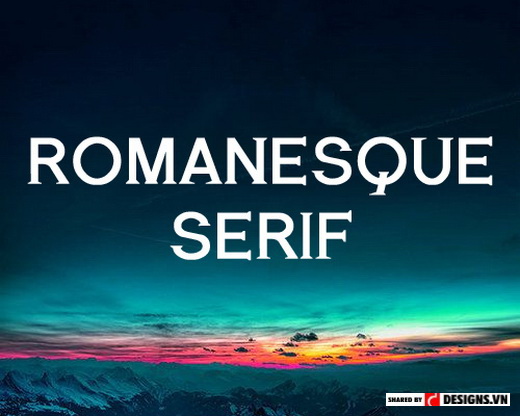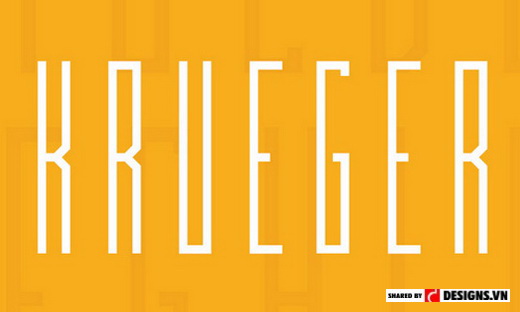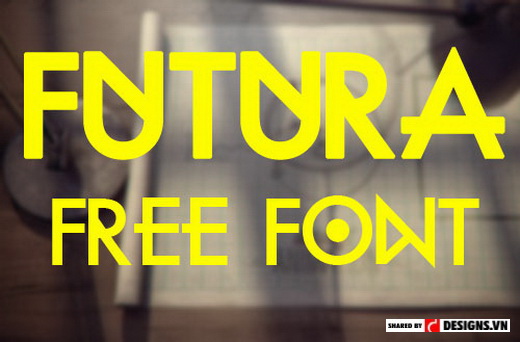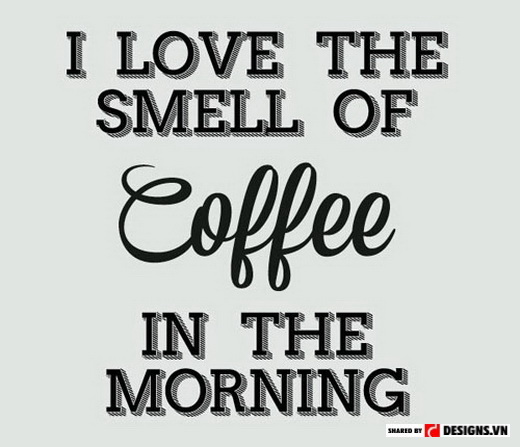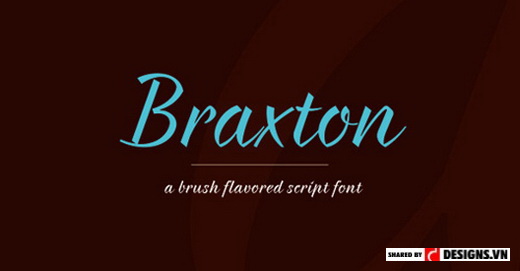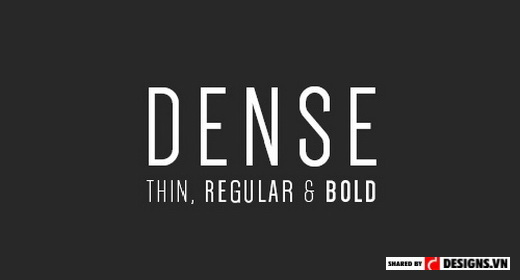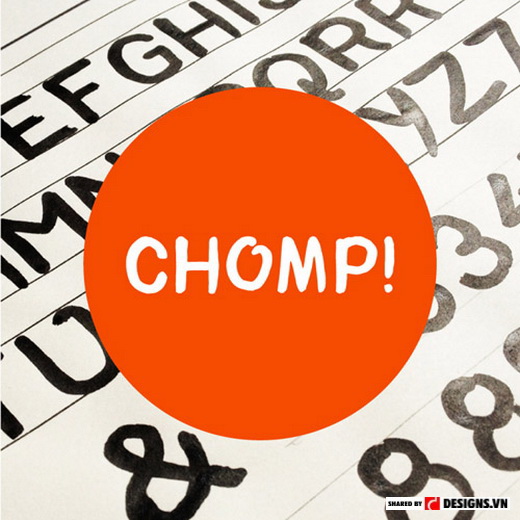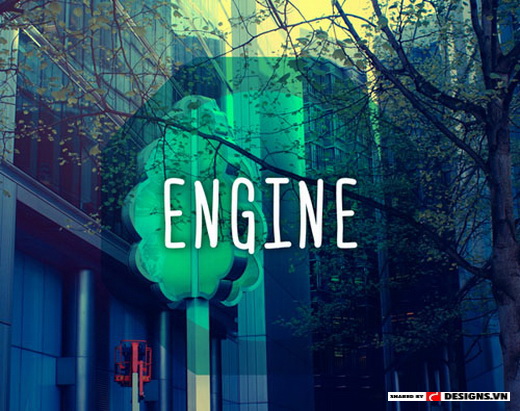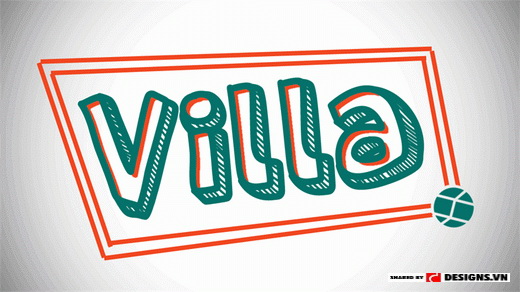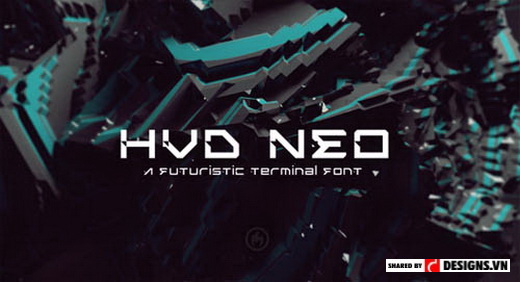
Download 26 font chữ đẹp chọn lọc
1. Romanesque Serif
Romanesque được phát triển từ font chữ Serif, dựa trên cảm hứng về những ký tự La Mã khắc trên bia đá của các ngôi mộ cổ. Download font chữ đẹp này.
2. Serious man
Font chữ cứng cáp dành cho các thiết kế poster và brochure. Download font chữ đẹp này.
3. Krueger
4. Elegant Ink
5. Futura
6. Mission Gothic
7. Moondance
Một font chữ rất đẹp mắt và sáng tạo mà bạn không nên bỏ qua. Download font chữ đẹp này.
8. Airbag
9. The enemy is public
Những kiểu chữ “chân dài” vẫn luôn được được yêu thích và ứng dụng rất nhiều. Download font chữ đẹp này.
10. Braxton
Một font chữ cực đẹp và dễ sử dụng này. Download font chữ đẹp này.
11. Quirky nots
12. Dense
Font chữ đơn giản mà designer nào cũng nên sở hữu. Download font chữ đẹp này.
13. Nexa slab
13. Lourve